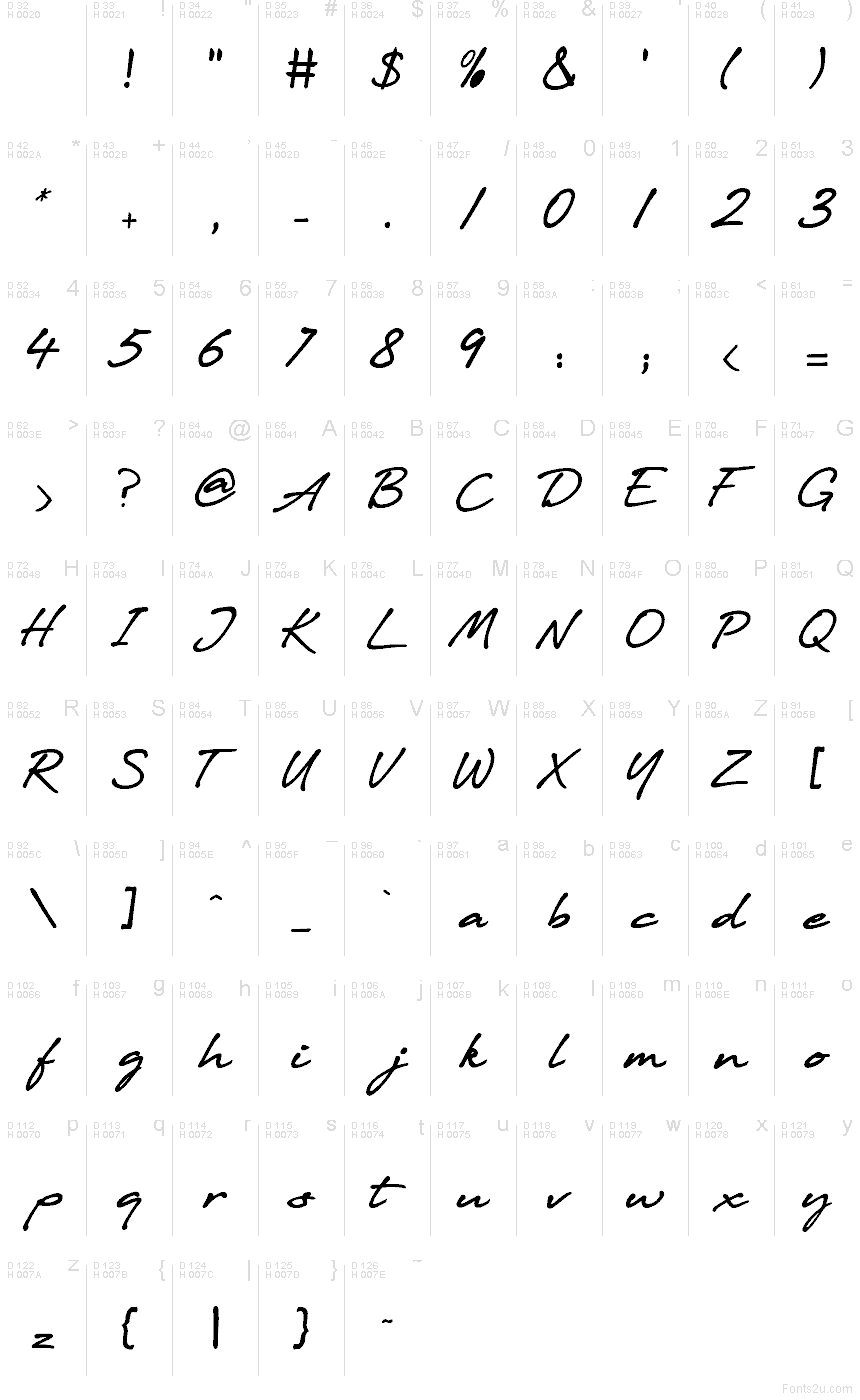
Le Jardin du Bonheur, ein kostenloser Handschrift-Font von BlackFridayFont, besticht durch den fließenden Schwung einer schnellen Unterschrift und einen leicht romantischen, französisch angehauchten Charme. Die Buchstaben werden von langen An- und Verbindungsstrichen getragen, während abgerundete Schlaufen und ein breiter Pinselrhythmus für einen entspannten statt verspielten Look sorgen.
Er fügt sich wunderbar in Boutique-Branding, Café-Speisekarten, Grußkarten, Produktverpackungen und Social-Media-Überschriften ein, bei denen ein Name oder kurzer Satz eine persönliche, elegante Note braucht. Als kostenloser Font eignet er sich zudem hervorragend für Cover-Lines, Monogramme und Einladungsköpfe, da die weitläufigen An- und Ausstriche selbst kurzen Wörtern eine grazile Präsenz verleihen.